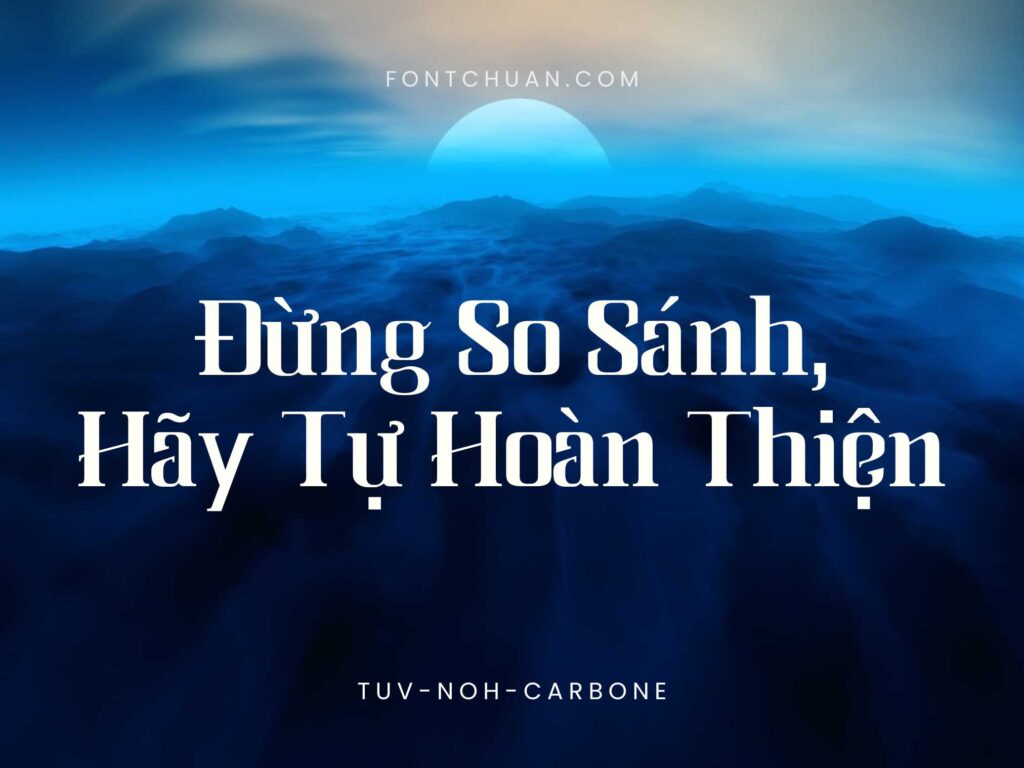
Font TUV Noh Carbone Việt Hóa
NOh Carbone là một font chữ serif với hơn 250 ký tự, bao gồm chữ in hoa, chữ in thường, số, ký tự đặc biệt và dấu câu. Được thiết kế bởi Nach Oh! và phát hành bởi OhType! vào năm 2013, font này thích hợp cho các thiết kế ở kích thước vừa và lớn, với độ tương phản cao, mang lại sự mạnh mẽ và độc đáo. NOh Carbone đã được Việt hóa để hỗ trợ tiếng Việt bởi Thùy Uyên, giúp người dùng Việt Nam dễ dàng áp dụng trong các dự án thiết kế. Font này được sưu tầm và chia sẻ bởi thành viên của Font Chuẩn, đáp ứng nhu cầu sử dụng đa dạng trong cộng đồng thiết kế.
Đặc điểm thiết kế của NOh Carbone bao gồm các chi tiết tinh tế và độ tương phản cao, tạo cảm giác sang trọng và hiện đại. Font này phù hợp cho các ứng dụng như thiết kế tiêu đề, logo, poster và các dự án sáng tạo khác. Ngoài ra, NOh Carbone cũng có thể được khai thác như một font chữ Trung Thu, mang lại sự ấn tượng và độc đáo trong các thiết kế liên quan đến sự kiện lễ hội, thiệp mời hay ấn phẩm truyền thông. Các ngành nghề phù hợp bao gồm quảng cáo, giáo dục và công nghệ.
Bên cạnh khả năng ứng dụng đa dạng cho các ấn phẩm Trung Thu, NOh Carbone còn rất linh hoạt khi sử dụng trong các dịp lễ hội khác. Với các font chữ Tết, nhà thiết kế có thể tạo ra thiệp mừng, lịch Tết hay banner quảng cáo mang phong cách sang trọng nhưng vẫn đậm chất truyền thống. Đồng thời, phiên bản Font chữ Halloween của NOh Carbone cũng mở ra cơ hội cho các dự án chủ đề Halloween, từ poster, tiêu đề đến các ấn phẩm quảng cáo, giúp các thiết kế thêm sinh động và bắt mắt. Nhờ sự đa dụng này, NOh Carbone trở thành lựa chọn lý tưởng cho nhiều lĩnh vực như quảng cáo, giáo dục, sự kiện và công nghệ, mang lại hiệu quả thẩm mỹ cao và sự chuyên nghiệp trong từng sản phẩm.